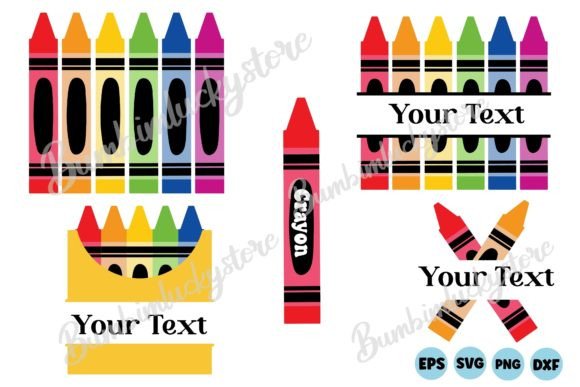
Crayon Split Monogram SVG
Crayon Split Monogram SVGのような高品質の素材をお探しの場合、このプレミアムパッケージはクリエイティブなプロジェクトに素晴らしい選択です。
精密に作られたCrayon Split Monogram SVGは、クリーンなベクター、滑らかなタイポグラフィ、そして安心のための商用ライセンスを提供します。
POD(オンデマンド印刷)製品、結婚式の招待状、またはソーシャルメディアのグラフィックを作成している場合でも、Crayon Split Monogram SVGは理想的です。